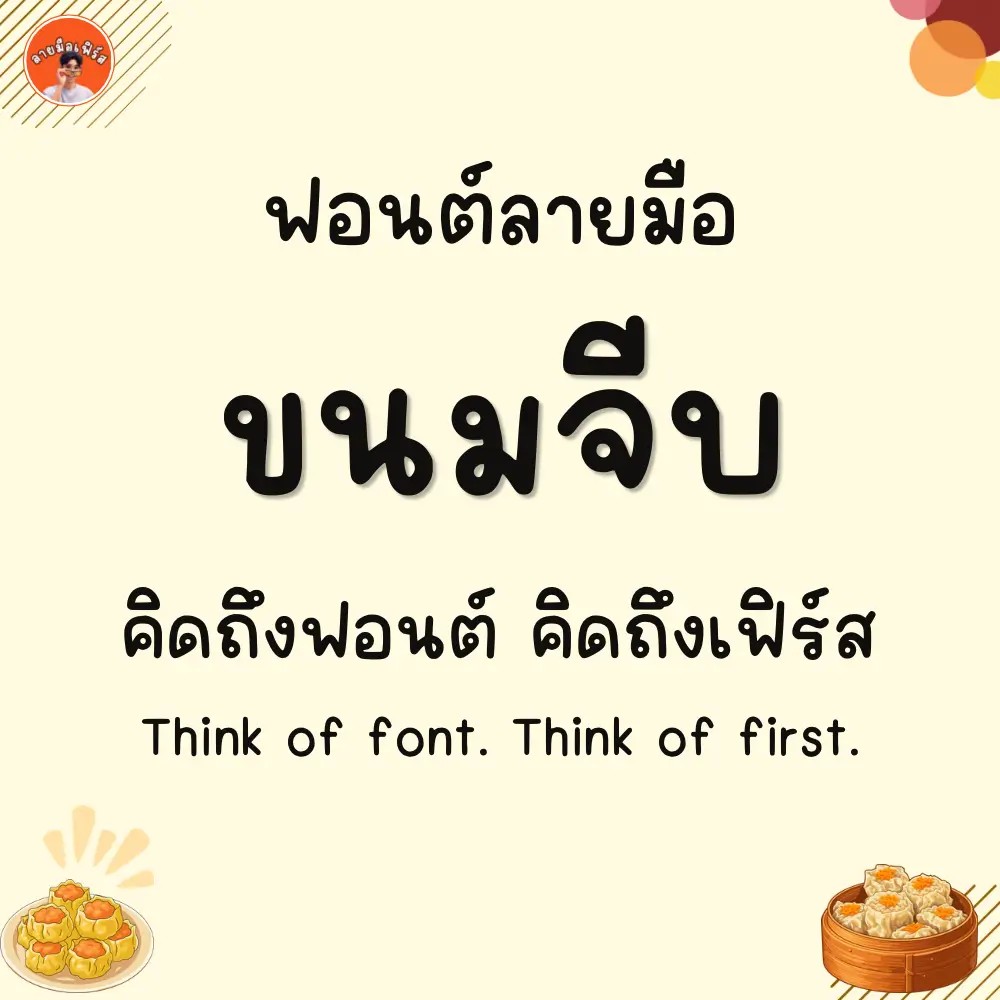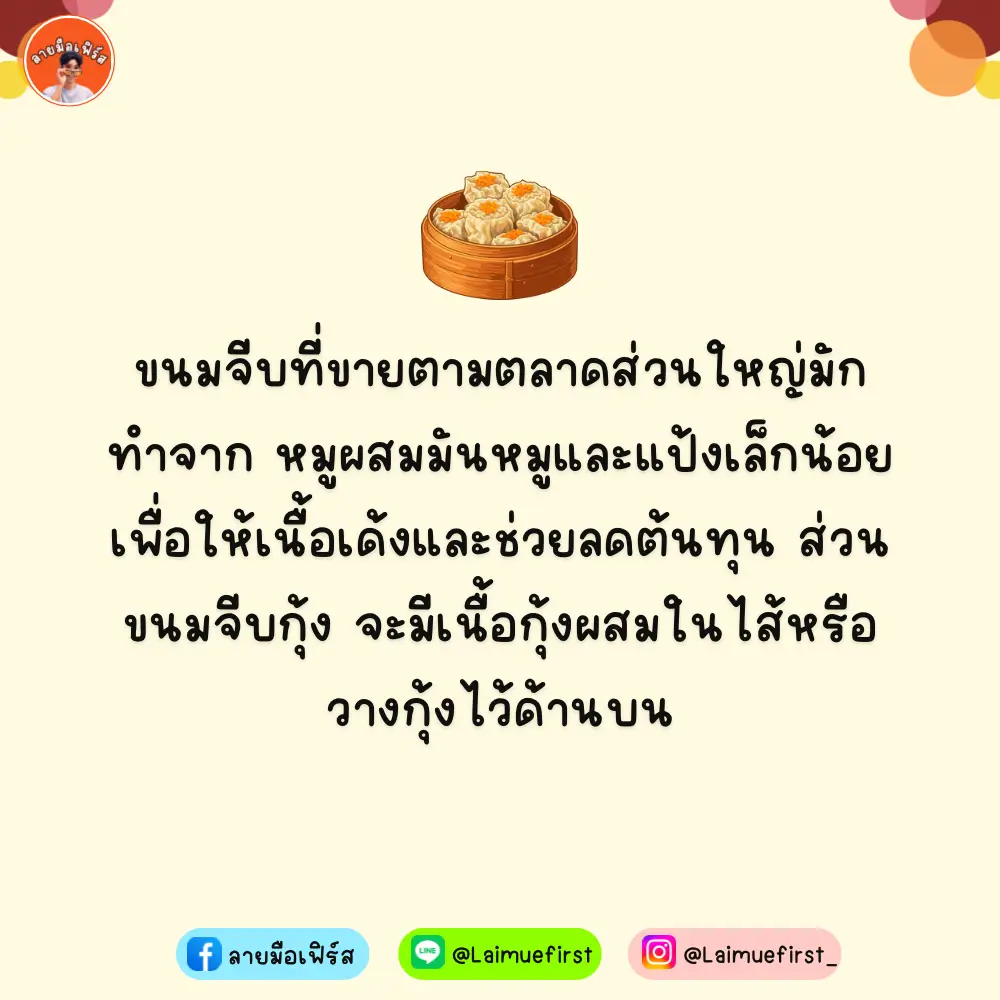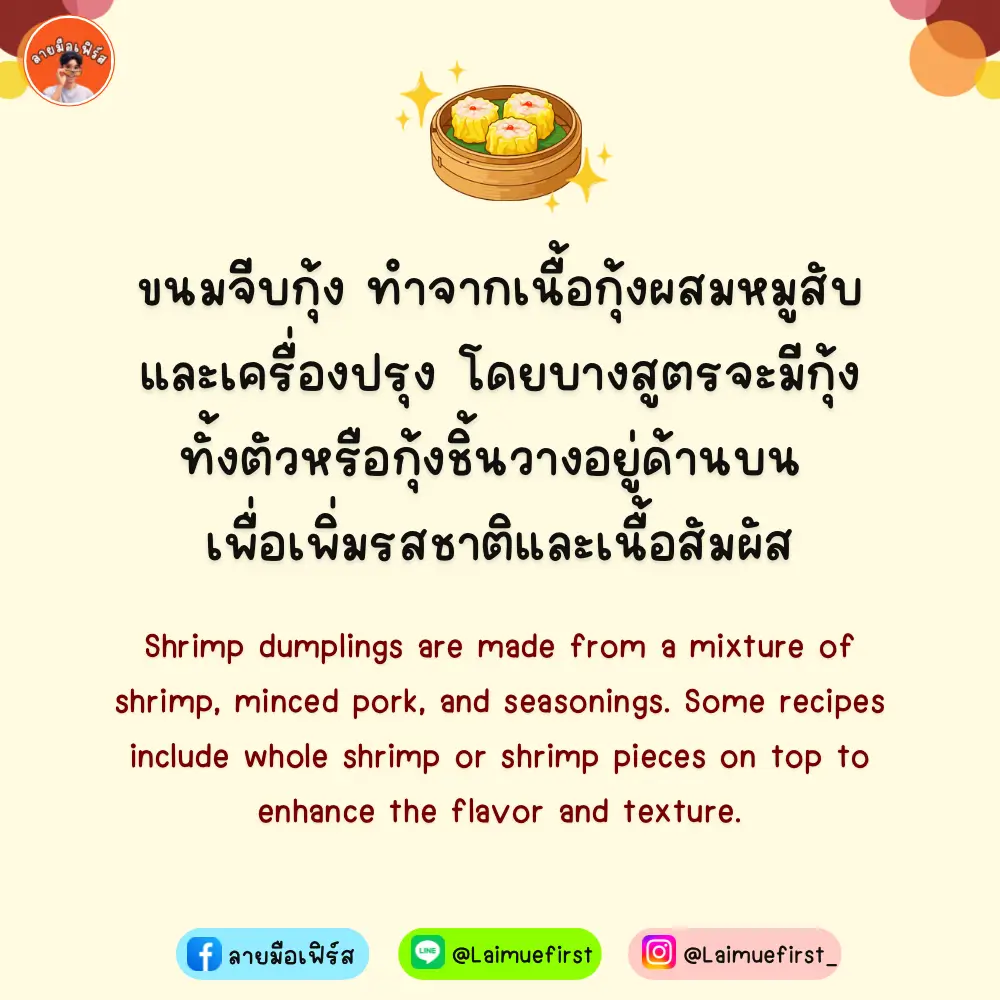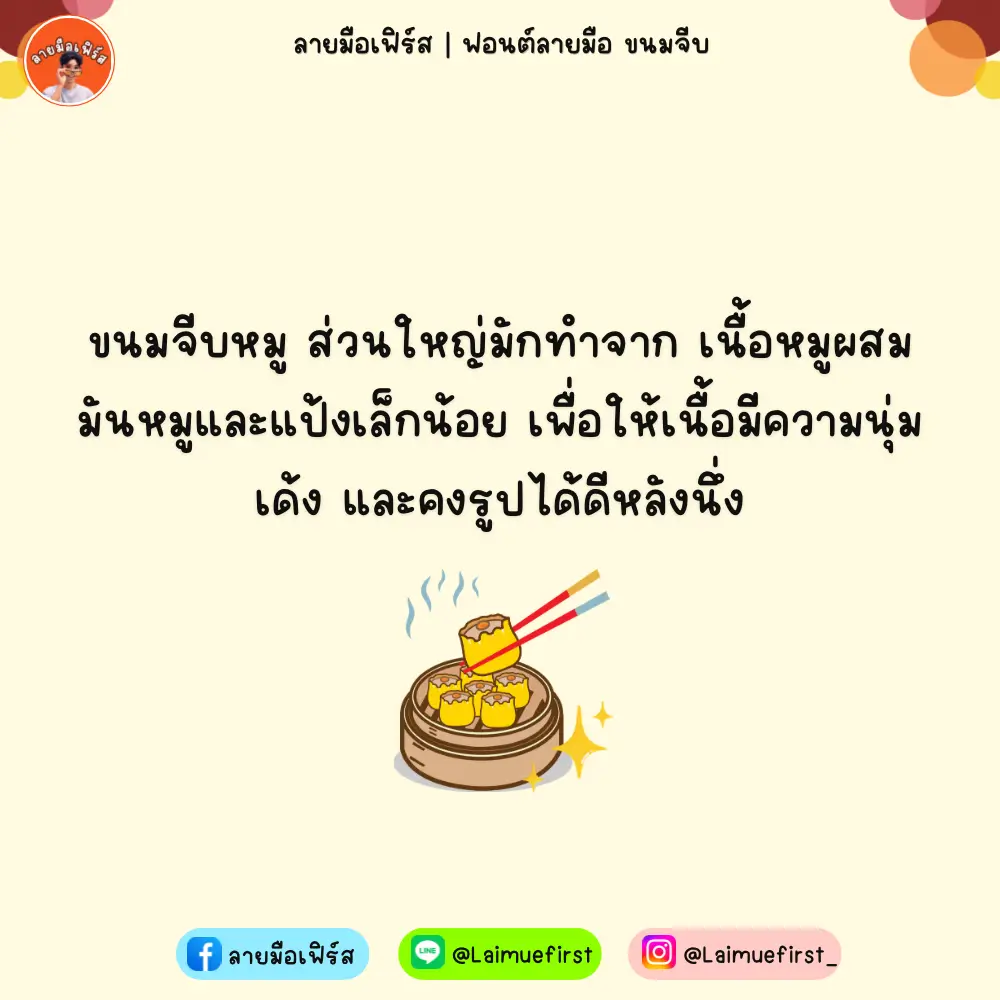
ฟอนต์ลายมือ ขนมจีบ (LMF Khanomjeeb) – แจกฟรีสำหรับทดลองใช้งานแบบส่วนตัว เวอร์ชันทดลอง (Demo)
- จะได้รับฟอนต์ 3 ขนาด (ปกติ/หนา/บาง)
- ตัวหนังสือปกติ ไม่มีตัวโปร่งปน
ขนมจีบ (LMF Khanomjeeb)